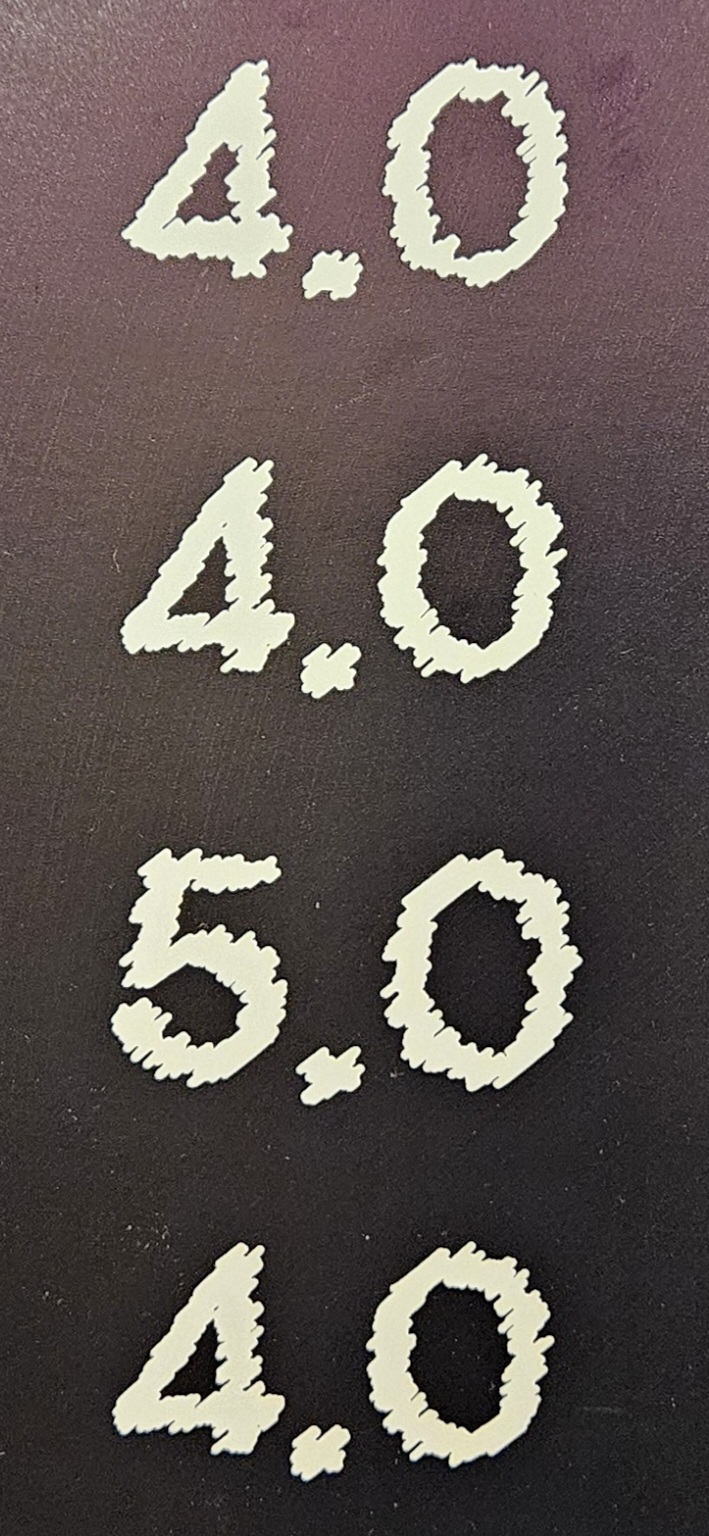
폰트알려주세요 cho*** 2024.05.24 숫자 폰트 알려주세요 댓글 0 등록 doo*** 글자깨서 scribble 효과 준것같은데요 2024-05-25 답글 달기 댓글 더보기 쉽고 빠르게 가장 비슷한 폰트를 알고 싶다면? 이미지로 검색하기
글자깨서 scribble 효과 준것같은데요